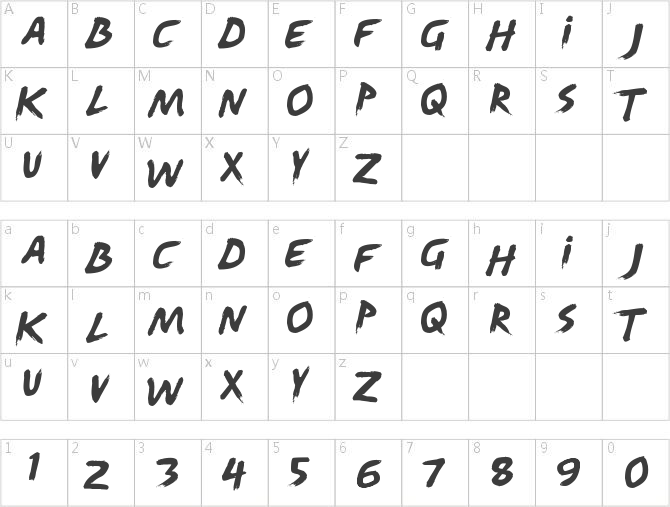
字體名稱: Lived M
Lived Mas NEW! With Numbers
Lived Mas NEW! With Numbers字體字庫是一款讓人賞心悅目、百看不厭的英文字體,適合各類廣告和產(chǎn)品包裝設(shè)計應(yīng)用,字體大小0.03MB,格式為ttf字體,上傳用戶是happy,作者/版權(quán)方為未知